Bài viết này tổng hợp danh sách 15 phông chữ Việt hóa mang phong cách sang trọng và đẳng cấp nhất năm 2026, được tuyển chọn kỹ lưỡng dành riêng cho thiết kế logo thương hiệu cao cấp. Nội dung đi sâu vào phân tích đặc điểm thẩm mỹ, tính ứng dụng và lý do vì sao các phông chữ này giúp nâng tầm giá trị hình ảnh cho doanh nghiệp.
15 Font Chữ Việt Hóa Sang Trọng 2026 Phù Hợp Thiết Kế Logo Cao Cấp
Trong lĩnh vực nhận diện thương hiệu, phông chữ không chỉ là phương tiện truyền tải thông tin mà còn là linh hồn của thiết kế. Một lựa chọn kiểu chữ đúng đắn có thể ngay lập tức thiết lập sự tin tưởng, khẳng định vị thế xa xỉ và tạo ra kết nối cảm xúc mạnh mẽ với khách hàng mục tiêu. Dưới đây là phân tích chuyên sâu về các nhóm phông chữ dẫn đầu xu hướng năm 2026.
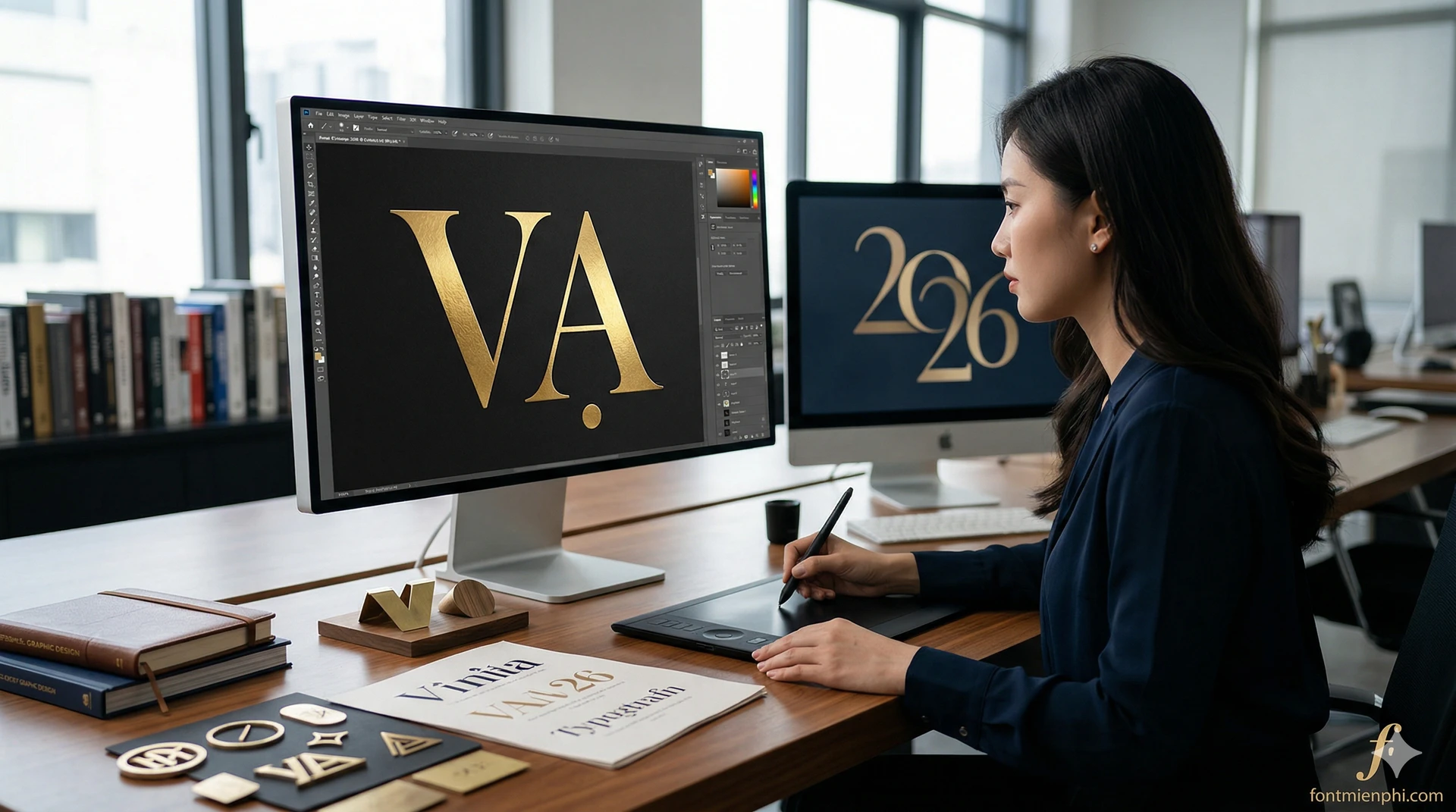
Tầm quan trọng của phông chữ trong thiết kế logo cao cấp
Thiết kế logo cho các phân khúc cao cấp như thời trang, mỹ phẩm, bất động sản hạng sang hay trang sức đòi hỏi sự tinh tế cực hạn. Phông chữ được chọn phải đáp ứng các tiêu chí về tỷ lệ vàng, độ tương phản nét thanh nét đậm chuẩn xác và khả năng hiển thị đa nền tảng. Khi một phông chữ được Việt hóa hoàn chỉnh, nó đảm bảo tính nhất quán về thẩm mỹ cho các thương hiệu nội địa mà không gặp lỗi hiển thị dấu tiếng Việt vốn thường gây mất cân đối trong bố cục.
1. Font Playfair Display – Sự giao thoa cổ điển và hiện đại
Playfair Display từ lâu đã là biểu tượng của sự thanh lịch. Với các nét dọc dày đặc trưng và nét ngang mảnh dẻ, nó gợi nhắc đến phong cách của các tạp chí thời trang danh tiếng từ thế kỷ 18 nhưng vẫn giữ được hơi thở đương đại.
Đặc điểm: Chân chữ sắc nét, độ tương phản cao.
Ứng dụng: Logo các hãng nước hoa, thời trang cao cấp hoặc tiêu đề tạp chí.
Ưu điểm: Bản Việt hóa xử lý các dấu sắc, huyền, hỏi rất tinh tế, không làm phá vỡ cấu trúc của các chữ cái thanh mảnh.
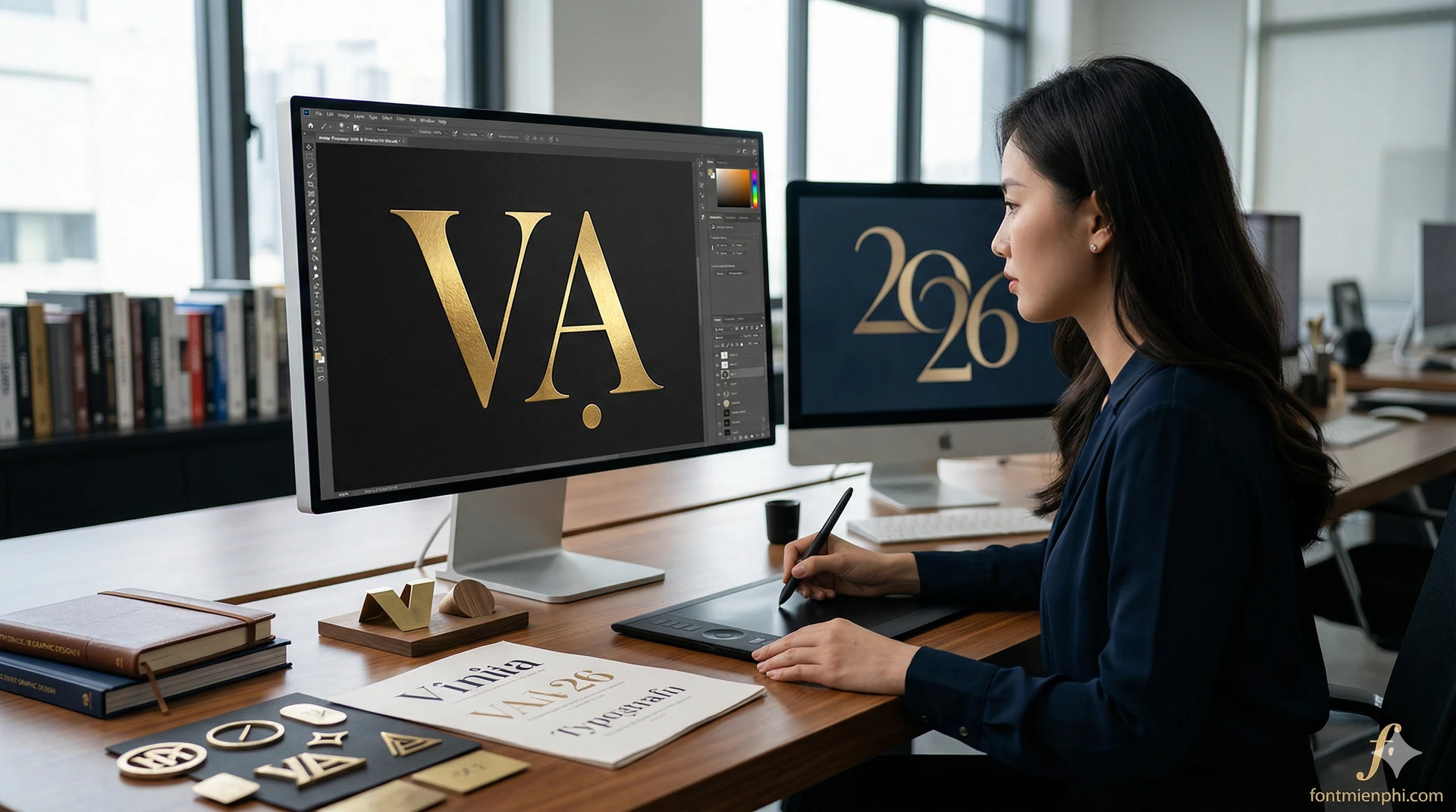
2. Font Montserrat – Tinh thần tối giản thượng lưu
Dù là phông chữ không chân (Sans Serif), Montserrat vẫn toát lên vẻ sang trọng nhờ sự tròn trịa và khoảng cách ký tự (kerning) hoàn hảo. Trong năm 2026, xu hướng tối giản vẫn chiếm ưu thế, và Montserrat là lựa chọn hàng đầu cho các thương hiệu công nghệ hoặc kiến trúc cao cấp.
Đặc điểm: Hình khối học mạnh mẽ, dễ đọc ở mọi kích thước.
Ứng dụng: Logo các đơn vị tư vấn thiết kế, startup công nghệ hạng sang.
Ưu điểm: Đa dạng về độ dày (weight) từ Thin đến Black, cho phép tùy biến linh hoạt.
3. Font Bodoni Moda – Đỉnh cao của sự xa xỉ
Bodoni Moda là phiên bản nâng cấp hoàn hảo cho các thiết kế cần sự nghiêm túc và đẳng cấp vượt thời gian. Những nét gạch ngang cực mảnh tạo ra một sự rung cảm thị giác đầy mê hoặc khi được đặt trên các tông màu tối như đen, vàng đồng hoặc xanh navy đậm.
Đặc điểm: Cấu trúc chữ đứng dọc, tạo cảm giác uy nghi.
Ứng dụng: Logo khách sạn 5 sao, các nhãn hàng rượu vang cao cấp.
Ưu điểm: Khả năng hiển thị sắc nét trên các chất liệu in ấn dập nổi hoặc mạ kim loại.
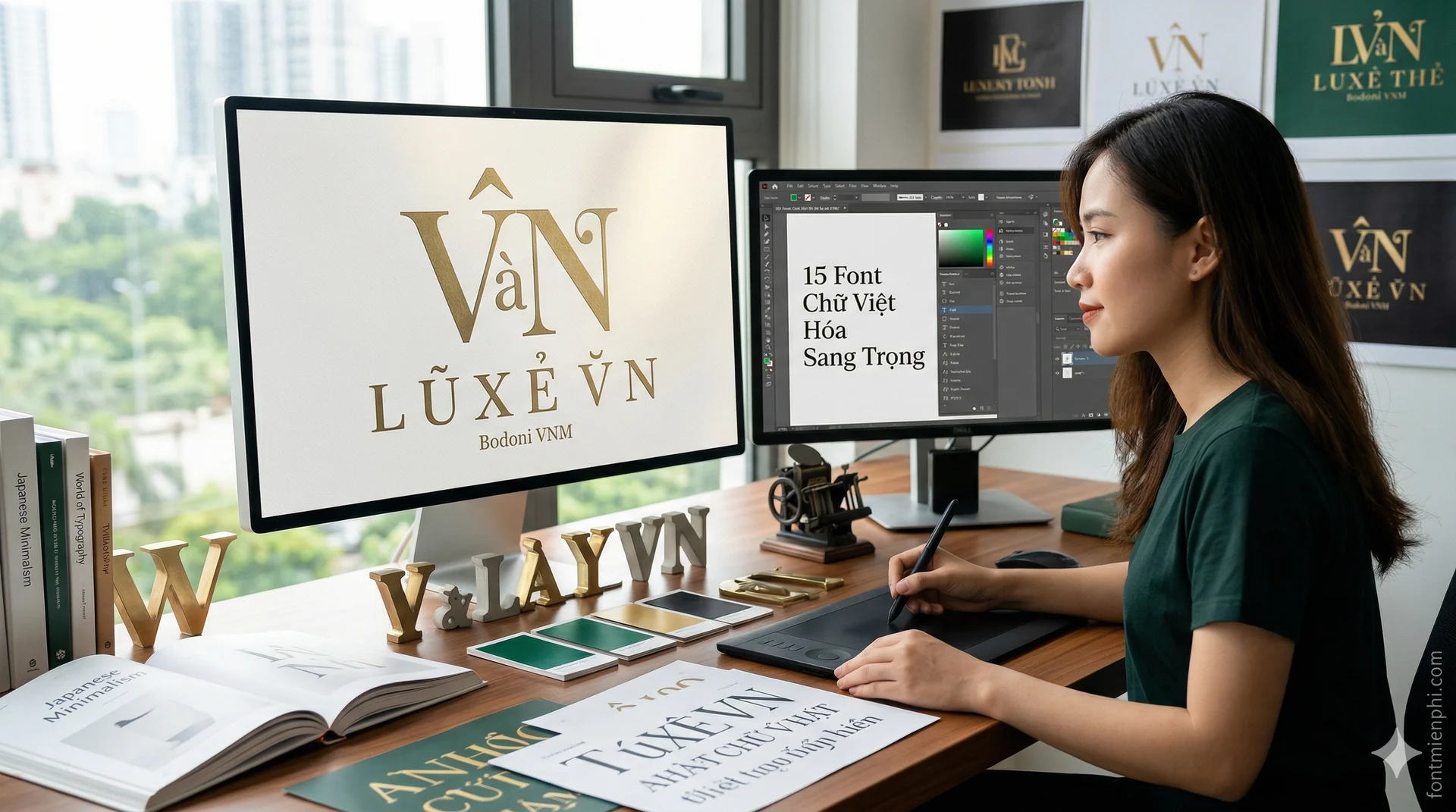
4. Font Cormorant Garamond – Vẻ đẹp của tri thức và quyền lực
Cormorant Garamond mang lại một cảm giác hoài cổ nhưng vô cùng sang trọng. Các đường cong của chữ cái được chau chuốt tỉ mỉ, tạo nên một dòng chảy mượt mà khi đọc. Đây là phông chữ lý tưởng cho các thương hiệu muốn nhấn mạnh vào bề dày lịch sử hoặc giá trị thủ công.
Đặc điểm: Chân chữ cong nhẹ, các chi tiết nhỏ được hoàn thiện tinh vi.
Ứng dụng: Logo các học viện nghệ thuật, spa chăm sóc sắc đẹp cao cấp.
Ưu điểm: Bản Việt hóa được tối ưu để các dấu không chồng chéo lên các nét chữ mảnh.
5. Font Cinzel – Cảm hứng từ kiến trúc La Mã
Lấy cảm hứng từ các bản khắc đá cổ đại, Cinzel mang trong mình hơi thở của lịch sử và sự bền vững. Đây là phông chữ hoàn hảo để tạo dựng hình ảnh một thương hiệu đáng tin cậy và vững chãi.
Đặc điểm: Toàn bộ là chữ in hoa (all caps), mang tính biểu tượng cao.
Ứng dụng: Logo các quỹ đầu tư, tập đoàn bất động sản hoặc trang sức cao cấp.
Ưu điểm: Khoảng cách giữa các chữ cái rộng tạo ra cảm giác thoáng đãng và sang trọng.
6. Font Be Vietnam Pro – Niềm tự hào chữ Việt hiện đại
Được thiết kế bởi chính người Việt, Be Vietnam Pro không chỉ chuẩn SEO mà còn cực kỳ phù hợp cho các thiết kế logo hướng đến sự hiện đại, trẻ trung nhưng vẫn không kém phần tinh tế.
Đặc điểm: Nét chữ trung tính, hiện đại, tối ưu cho hiển thị kỹ thuật số.
Ứng dụng: Các ứng dụng tài chính cao cấp, nền tảng thương mại điện tử xa xỉ.
Ưu điểm: Tương thích hoàn hảo với tiếng Việt, không cần điều chỉnh thủ công các dấu.
7. Font Lora – Sự mềm mại tinh tế
Lora là một phông chữ có chân mang nét đương đại, kết hợp hài hòa giữa sự thư pháp và các đường nét kỹ thuật số. Nó gợi lên sự ấm áp nhưng vẫn rất chuyên nghiệp.
Đặc điểm: Các đầu chân chữ hơi bo tròn, tạo cảm giác thân thiện.
Ứng dụng: Logo các nhãn hàng mỹ phẩm organic cao cấp, trà hoặc cà phê thượng hạng.
Ưu điểm: Hiệu quả cực tốt khi kết hợp với các hình vẽ minh họa nét mảnh.
8. Font Josefin Sans – Hình khối và sự thanh thoát
Việc lựa chọn phông chữ phù hợp là bước đi chiến lược trong việc xây dựng hình ảnh thương hiệu. Với danh sách 15 phông chữ Việt hóa sang trọng trên, các nhà thiết kế và chủ doanh nghiệp có thể dễ dàng tìm thấy giải pháp tối ưu để thể hiện đẳng cấp và giá trị cốt lõi của mình thông qua ngôn ngữ của kiểu chữ. Mỗi phông chữ mang một câu chuyện riêng, một cảm xúc riêng, và việc chọn đúng phông chữ chính là chìa khóa để mở cánh cửa đi vào tâm trí khách hàng thượng lưu.